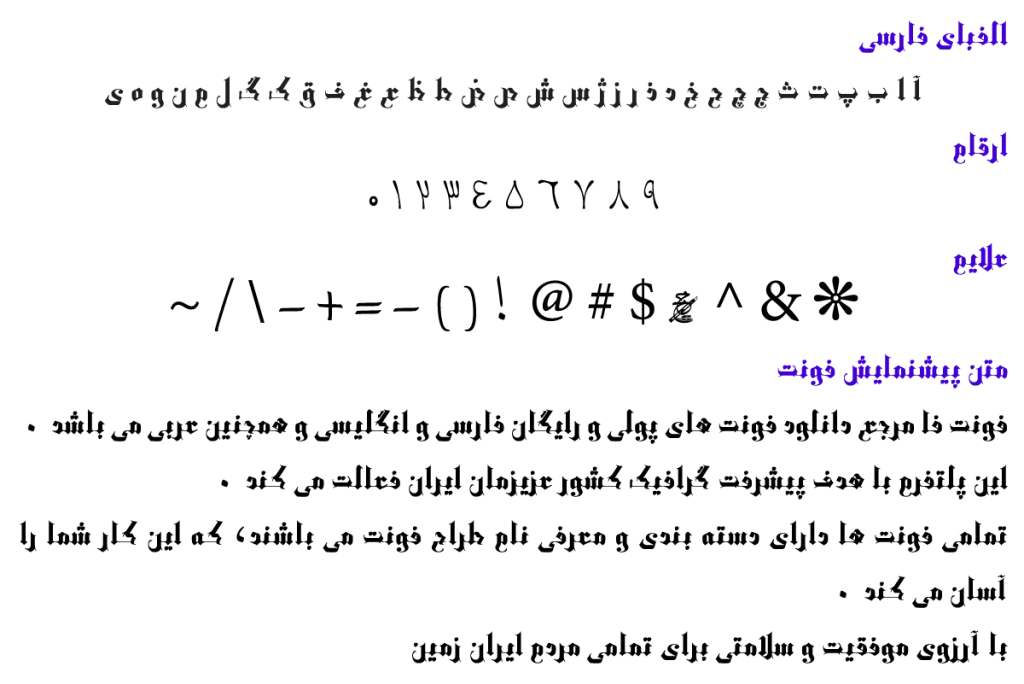
فونت فارسی سلیم – Persian SALIM
سال ساخت فونت: 1392
مجموعه فونت: فونت سری پرشین
طراح فونت: امیر حسین صدقی نوع فونت: فونت فانتزی
پیشنمایش فونت سلیم
توضیحات و معرفی فونت سلیم
فونت فارسی سلیم ( Persian SALIM ) از مجموعه فونت های سری پرشین می باشد، و نیز نوع فونت فانتزی می باشد.
فونت خوشگل مربوط توسط امیر حسین صدقی در سال 1392 طراحی و ساخته شده است.
و نیز فونت Persian SALIM در یک وزن معمولی است.
در تصویر زیر می توانید شعر زیبای «وطنم» را که با این قلم نوشته شده، تماشا کنید.